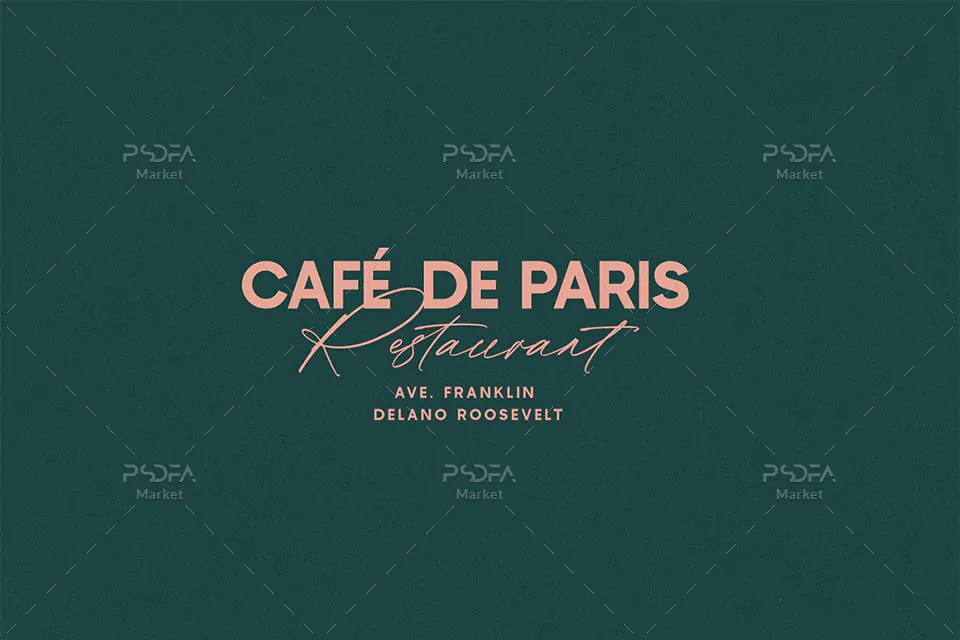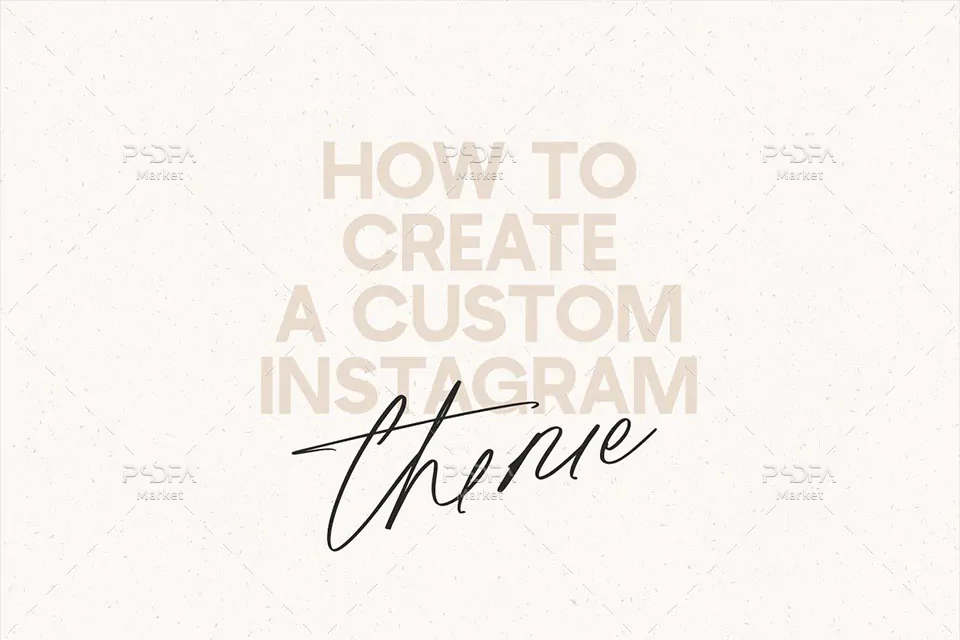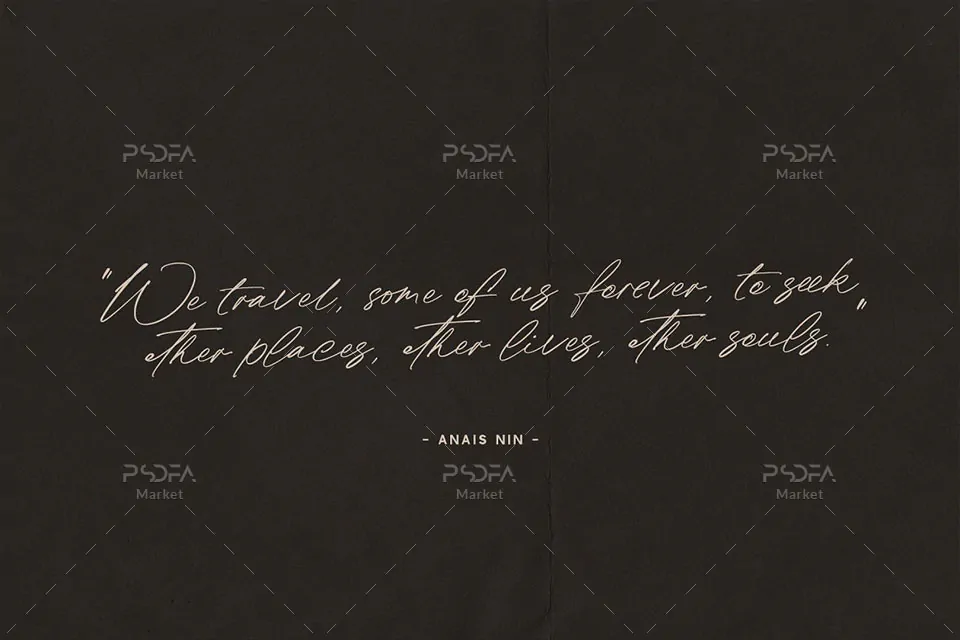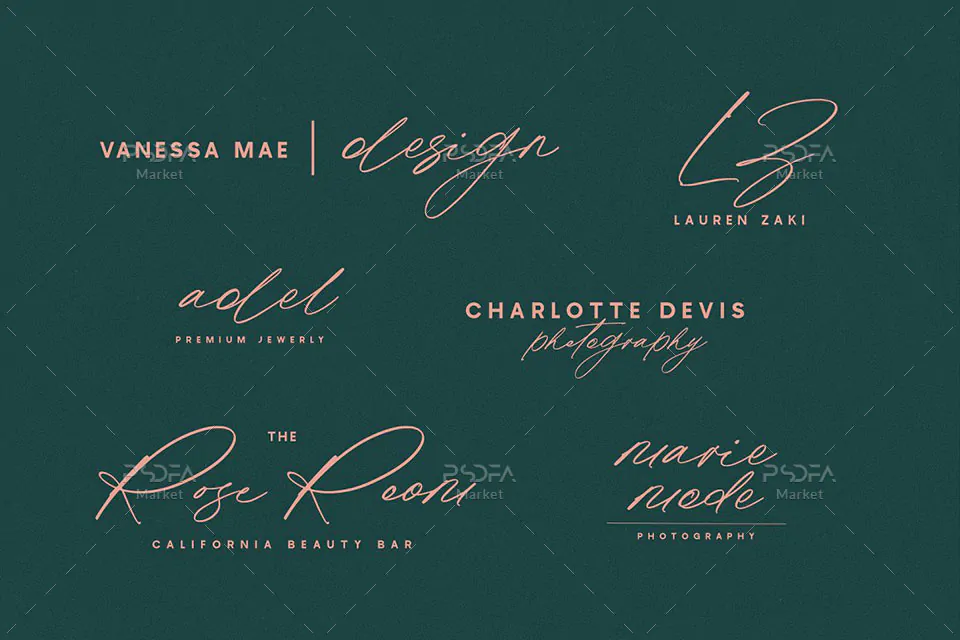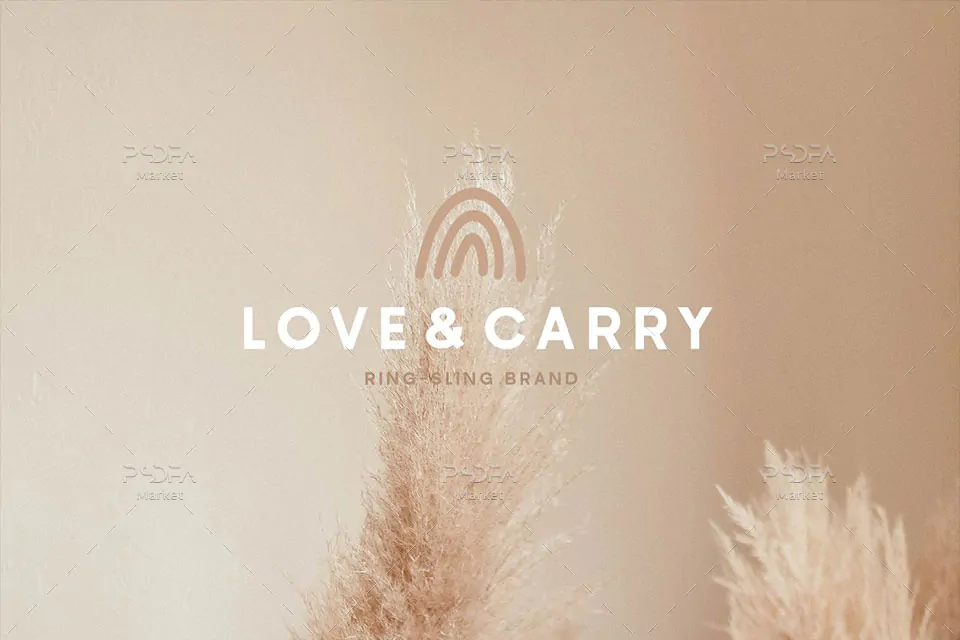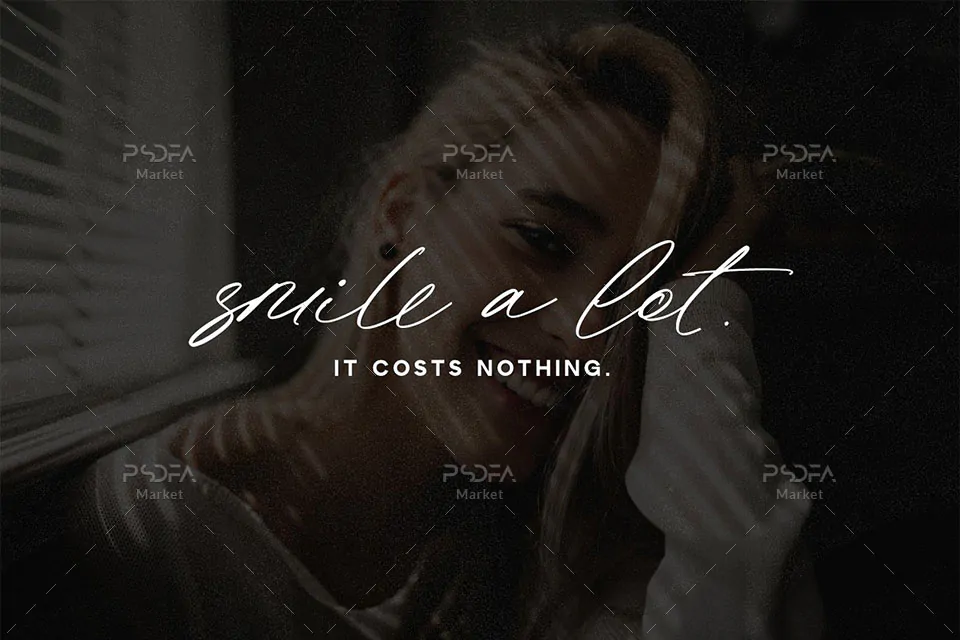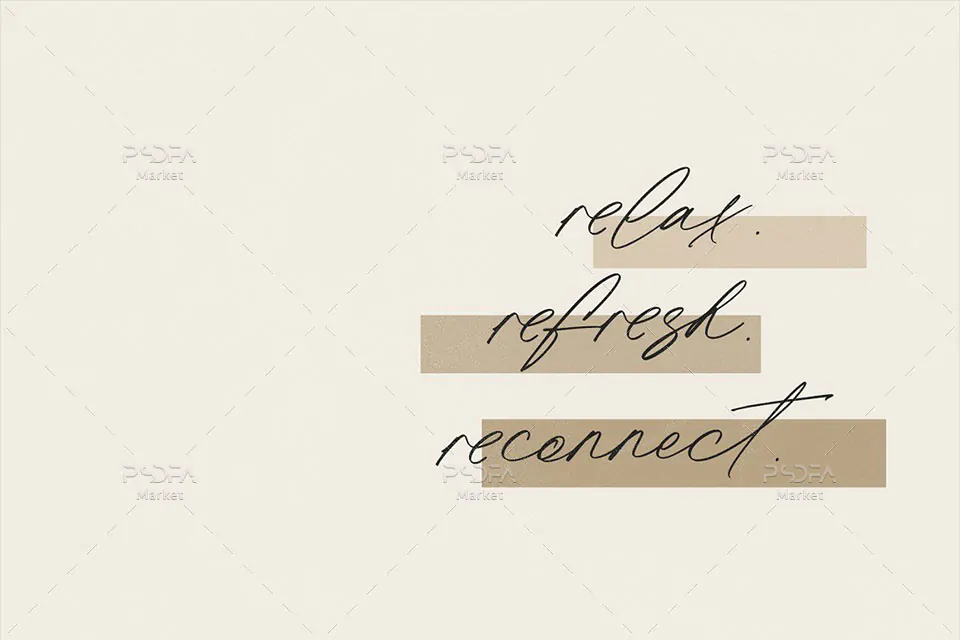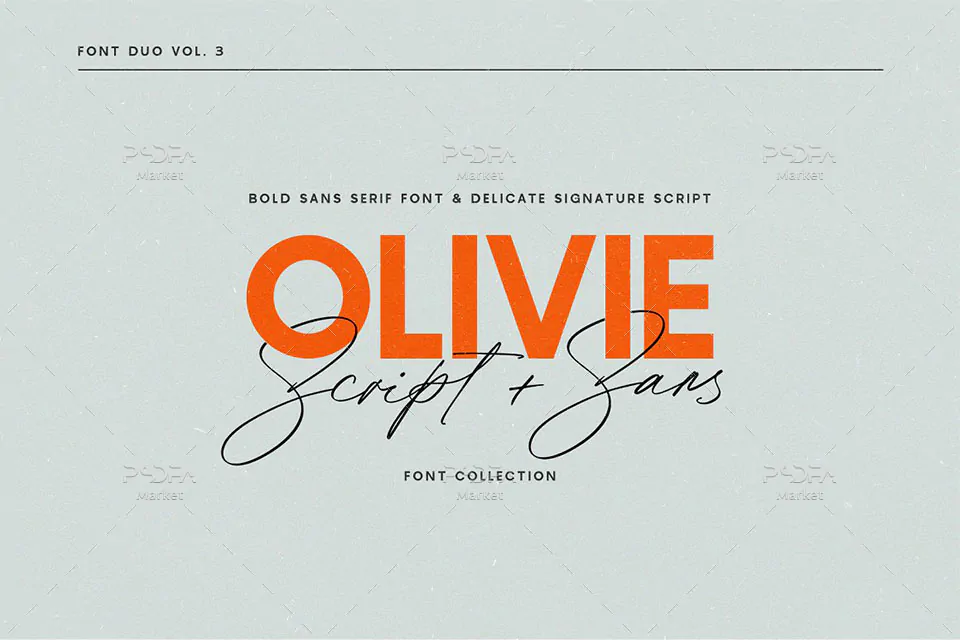
فونت اسکریپت دستنویس Olivie به همراه سریف فونت مجموعهای از 2 قلم فوق العاده زیبا است که مناسب جهت استفاده در طرحهای گرافیکی مختلف به خصوص طراحی انواع کارت، کاور آلبوم و … میباشند. این 2 فونت زیبا در قالب 6 فایل OTF, TTF, WOFF در فایل محصول قرار دارد که با نصب یکی از 2 فرمت ttf یا otf در پوشه فونتهای سیستم میتوانید از این فونت انگلیسی در تمام نرم افزارهای گرافیکی و تایپ متون همچون فتوشاپ، افتر افکت، پریمیر، ورد، پاورپوینت و … استفاده کنید.
فونت Olivie در وزن معمولی (Regular) طراحی شده است که میتوانید از آن در طراحی انواع کارت تبریک، کارت پستال، کارت ویزیت، کارت عروسی، کارت دعوت، طراحی لوگو، کاور آلبوم موزیک، طراحی انواع بنر، پوستر، تراکت، تقویم و دیگر طرحهای گرافیکی استفاده کنید. از نسخه woff این قلم نیز میتوانید در طراحی صفحات وب استفاده کنید.
- نام فونت: Olivie
- وزن: Regular